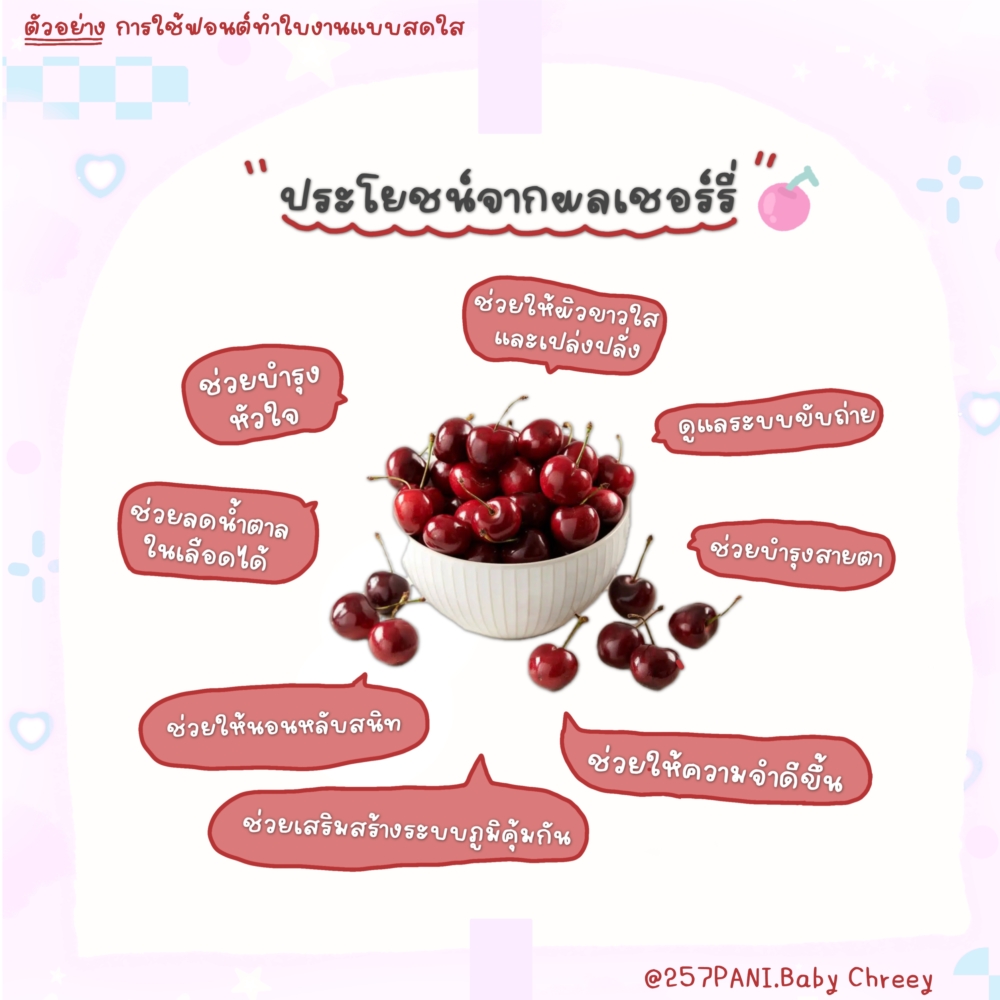
เบบี้เชอร์รี่
ฟอนต์แนวลายมือสดใส และมีความน่ารักไปเต็มไปหมด
แถม ฟอนต์อีโมจิไปด้วยอีกชุด
ชุดนี้บอกเลย ใช้คำว่าน่ารักได้เปลืองมาก
ชุดนี้ถึงจะเป็นแนวลายมือเด็ก แต่แอนทำให้อ่านง่าย ใช้ง่ายเหมือนเดิมค่ะ
ฟอนต์มี 4 ไฟล์ - น้ำหนัก บาง ปกติ หนา Cute